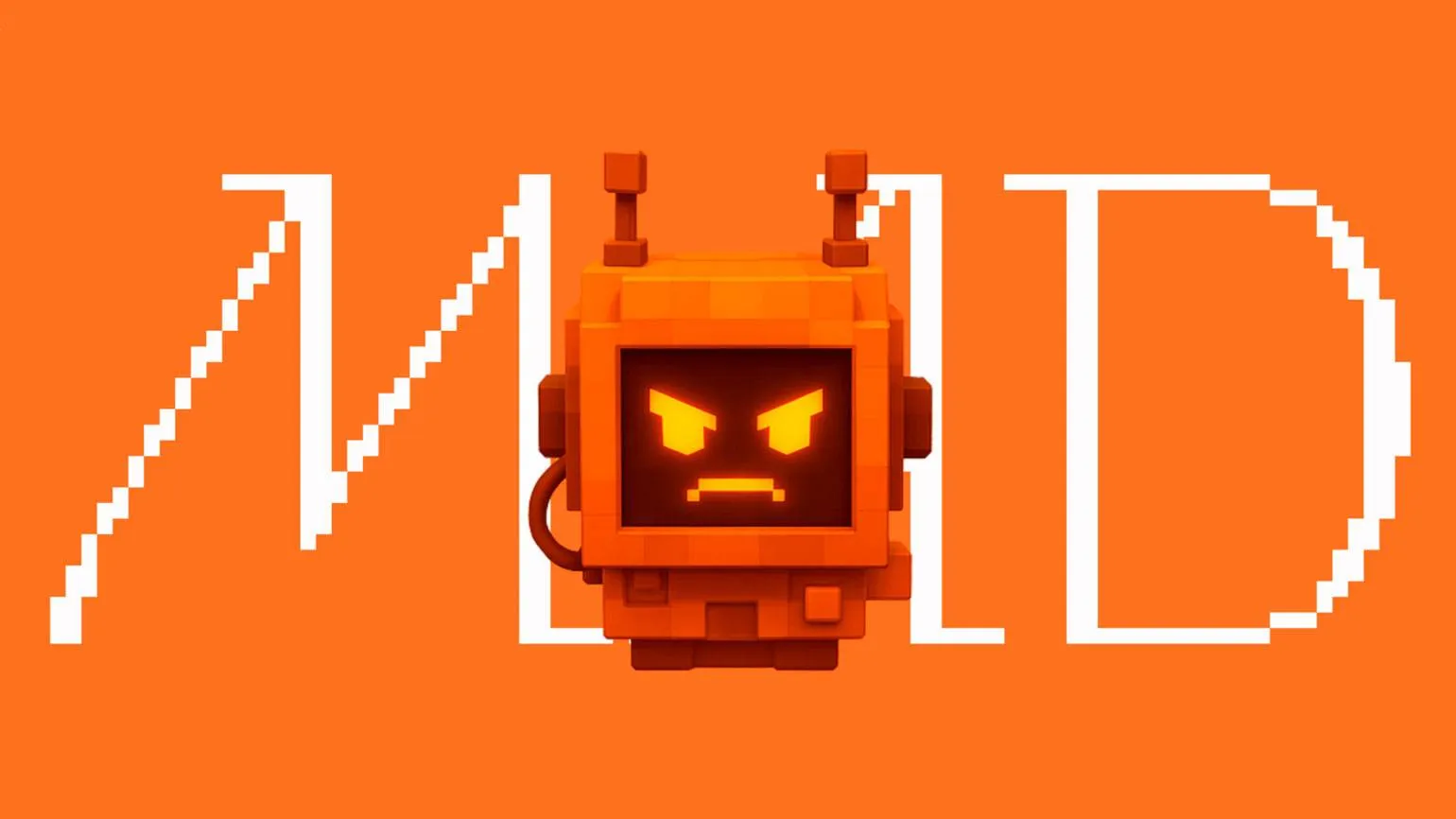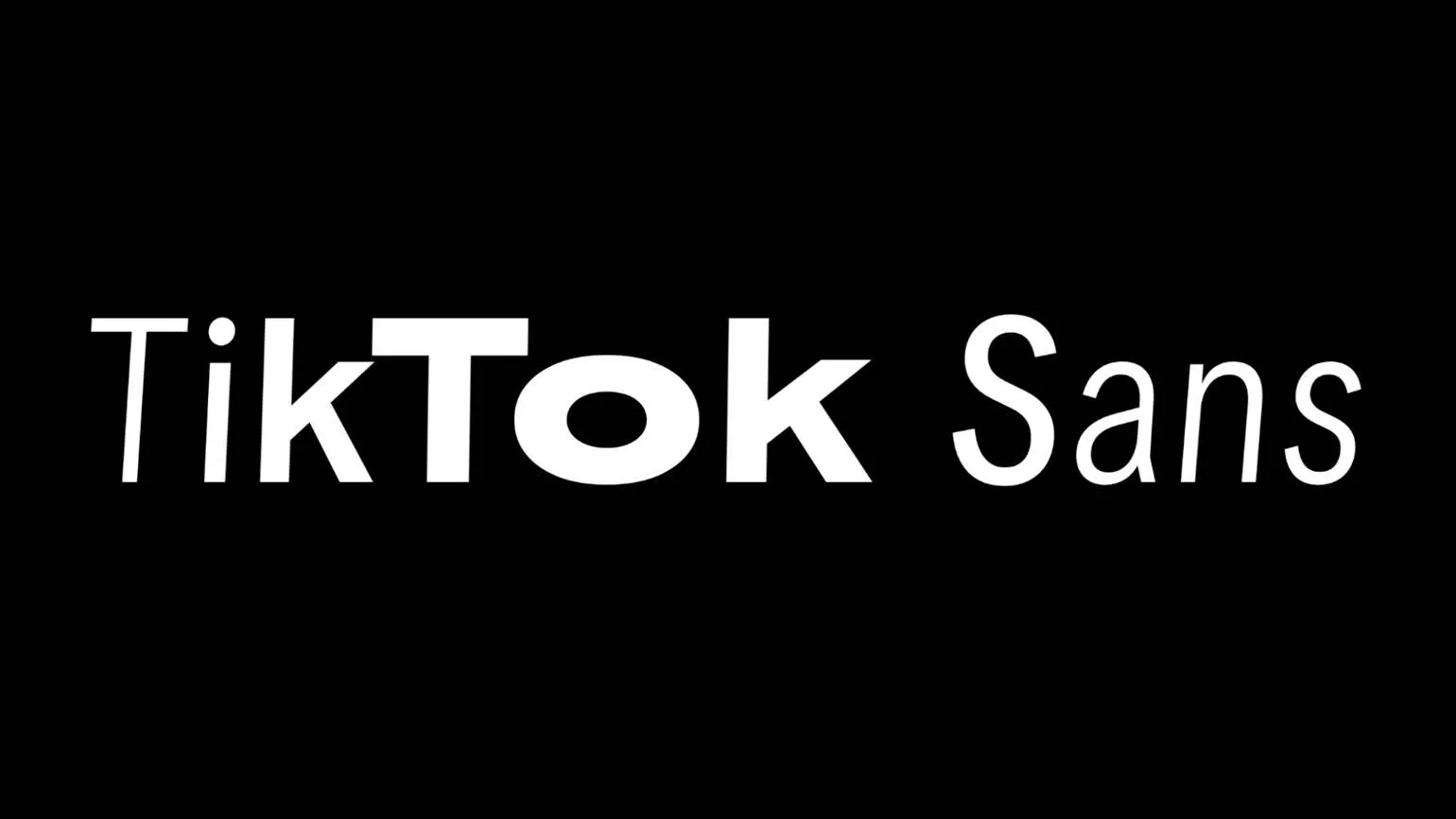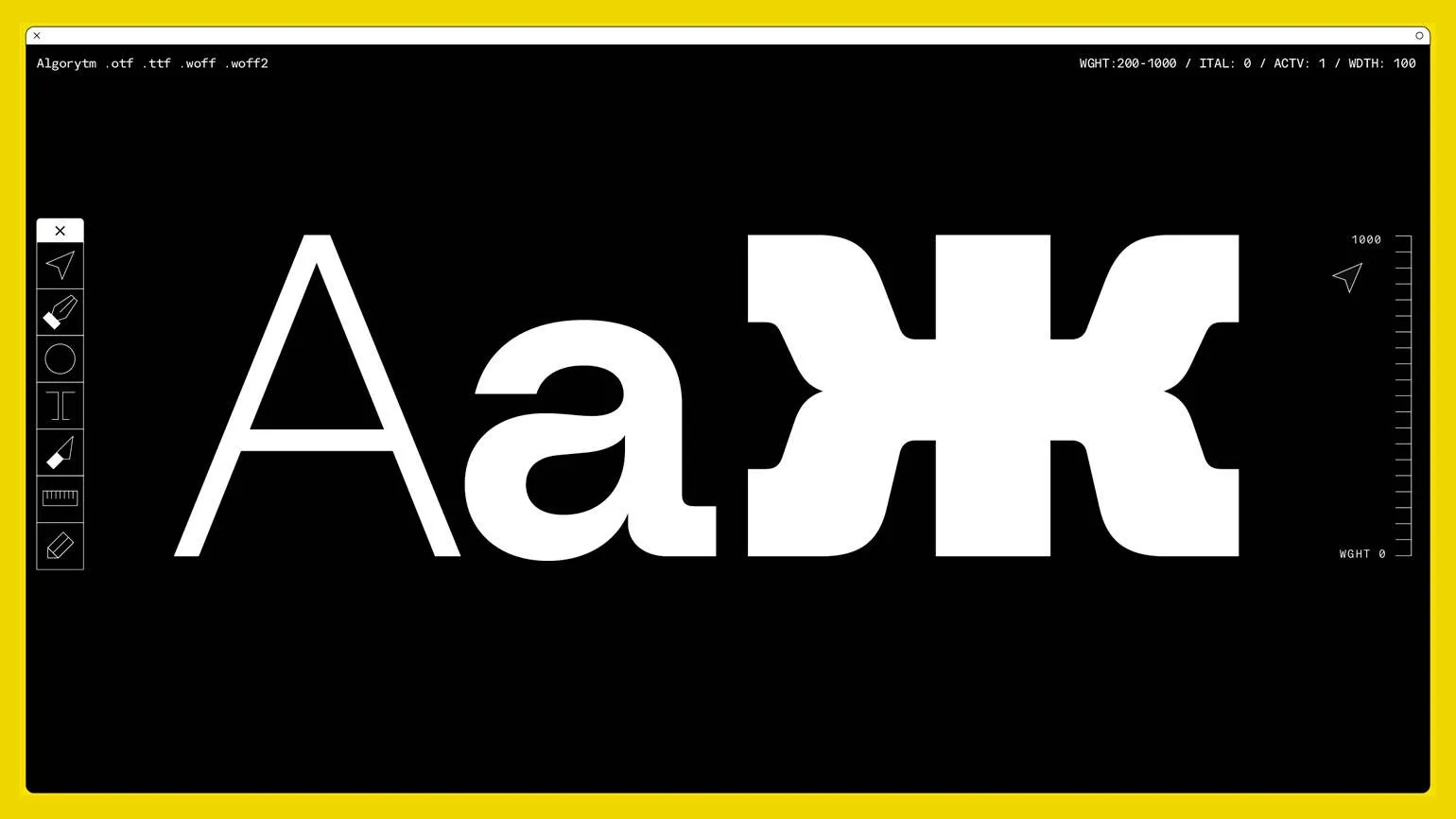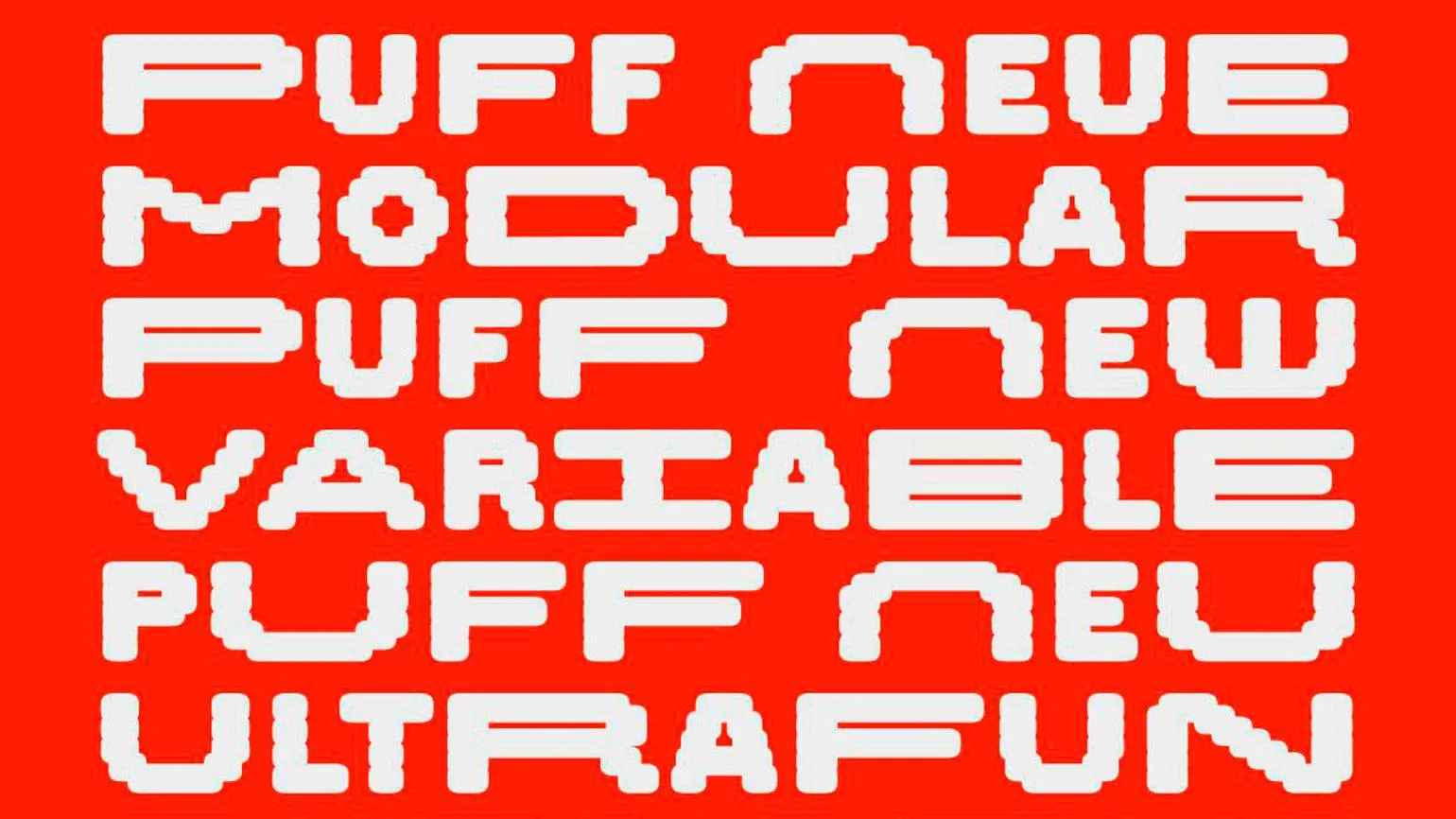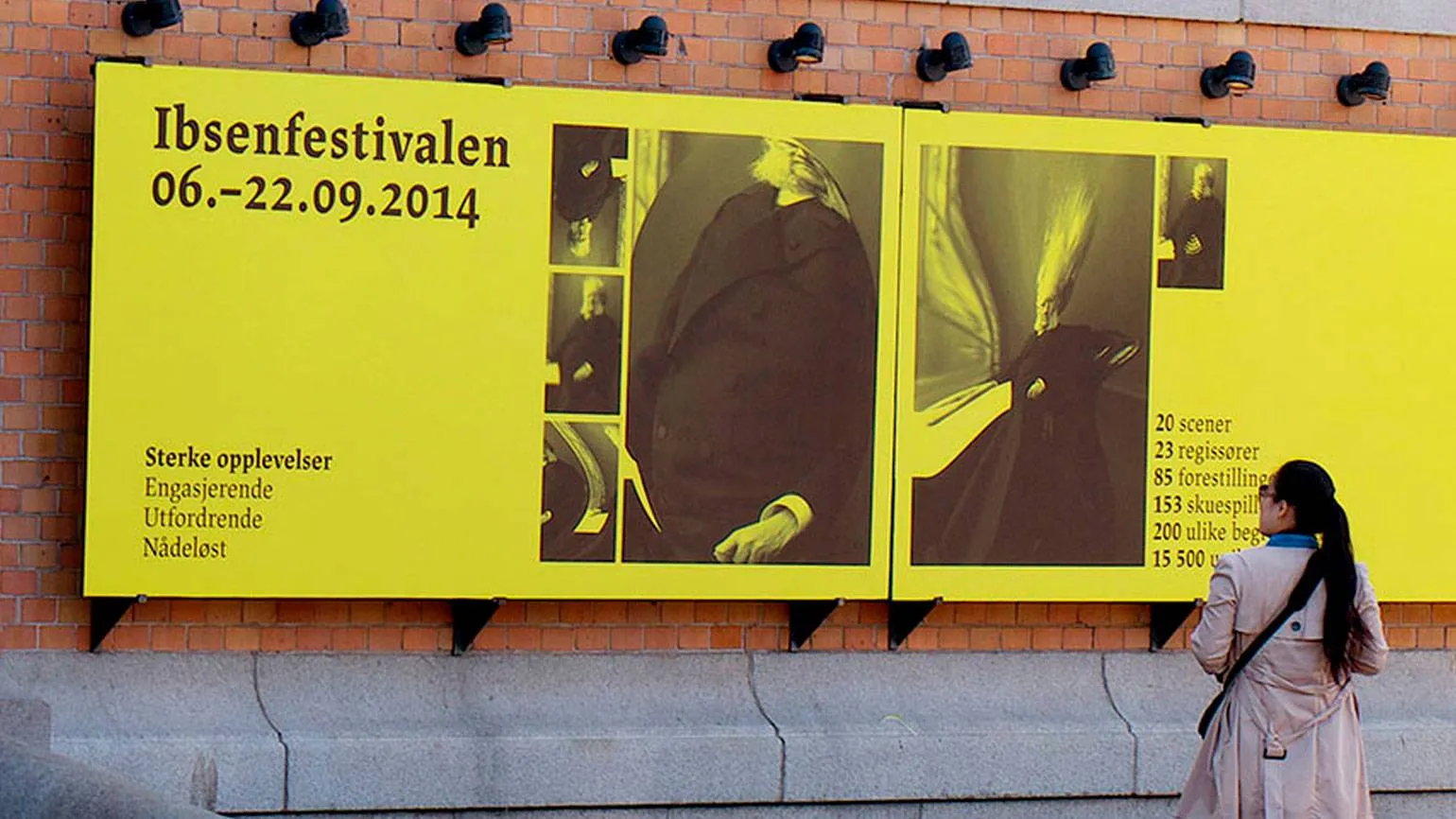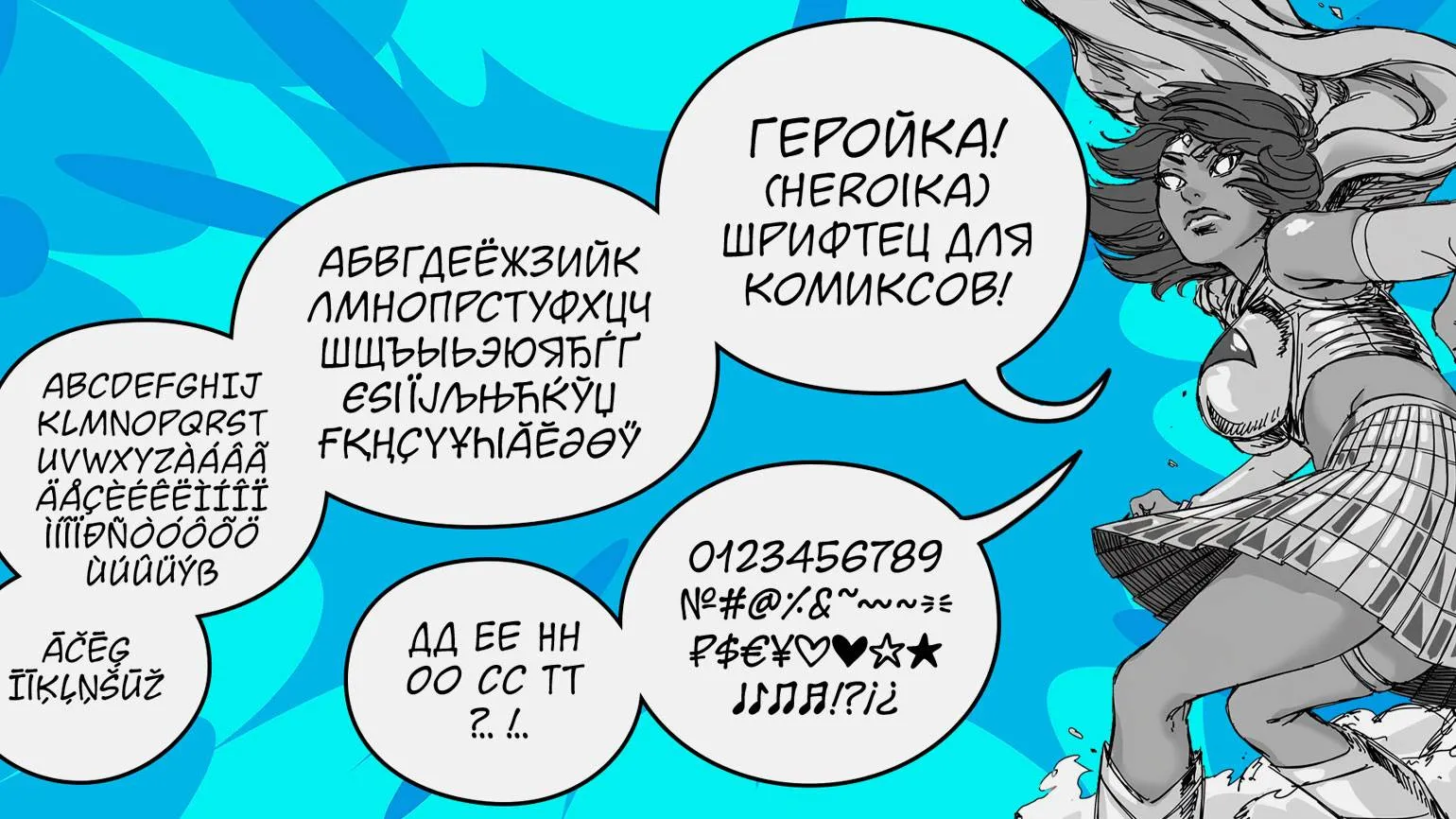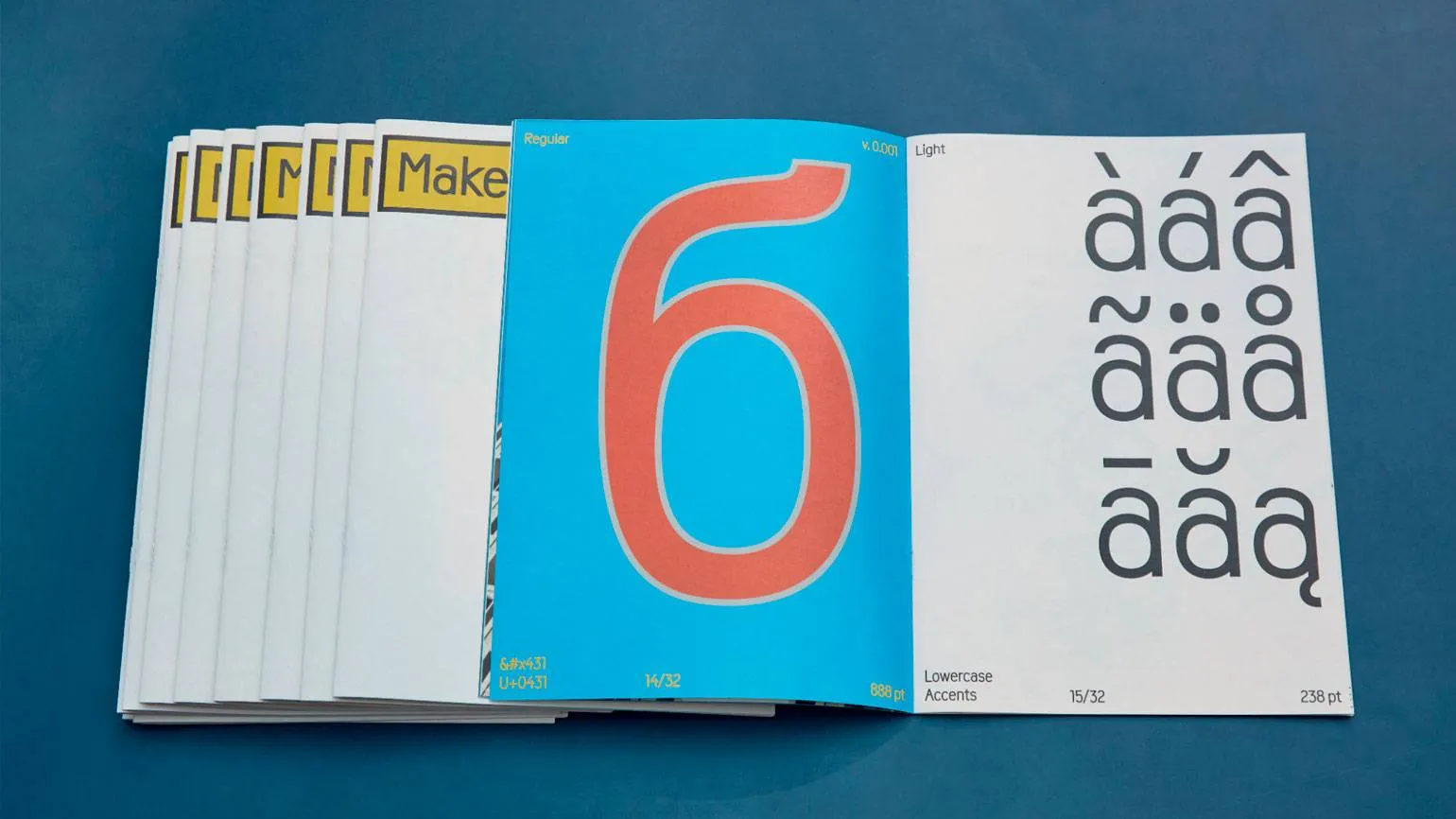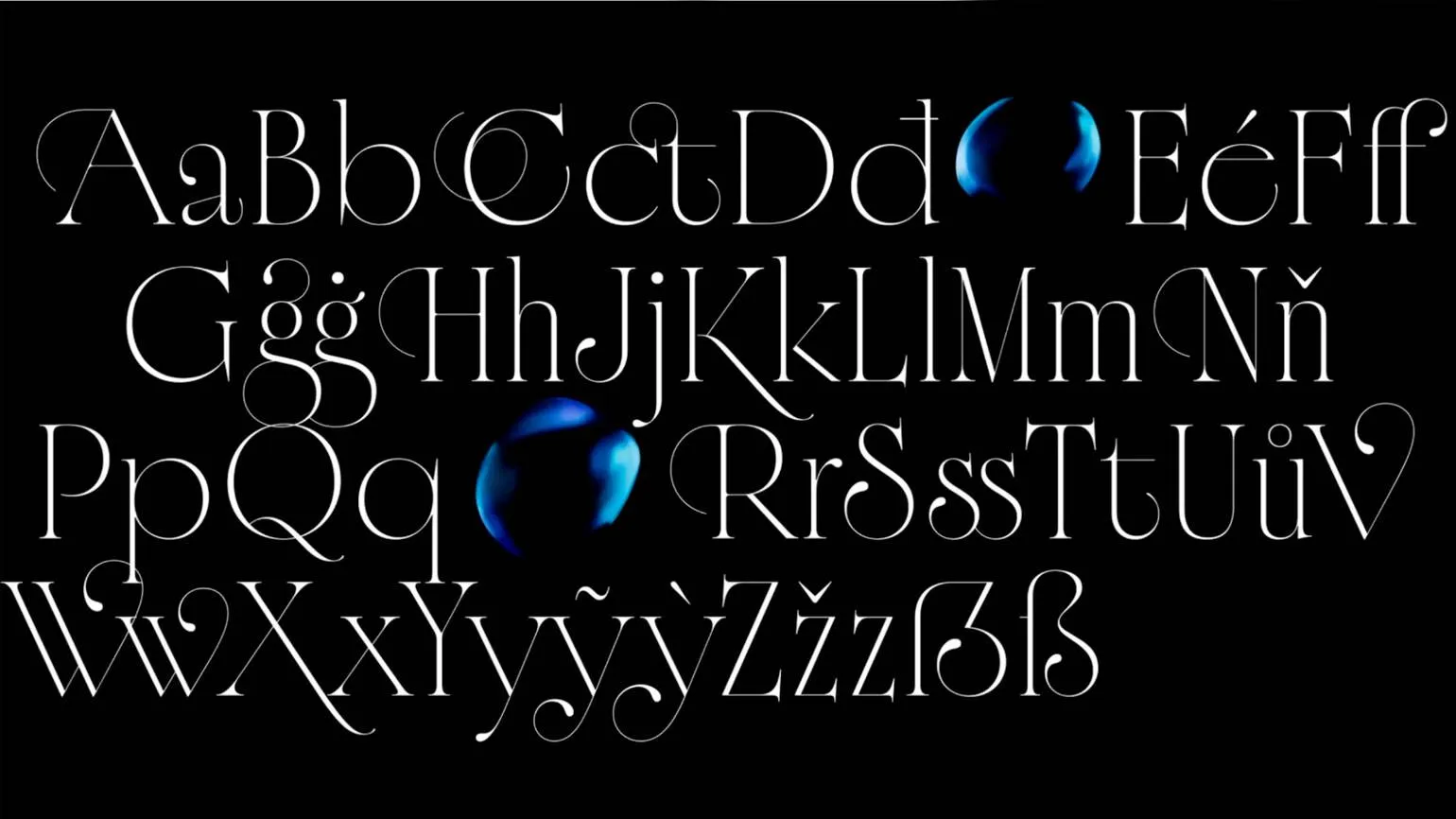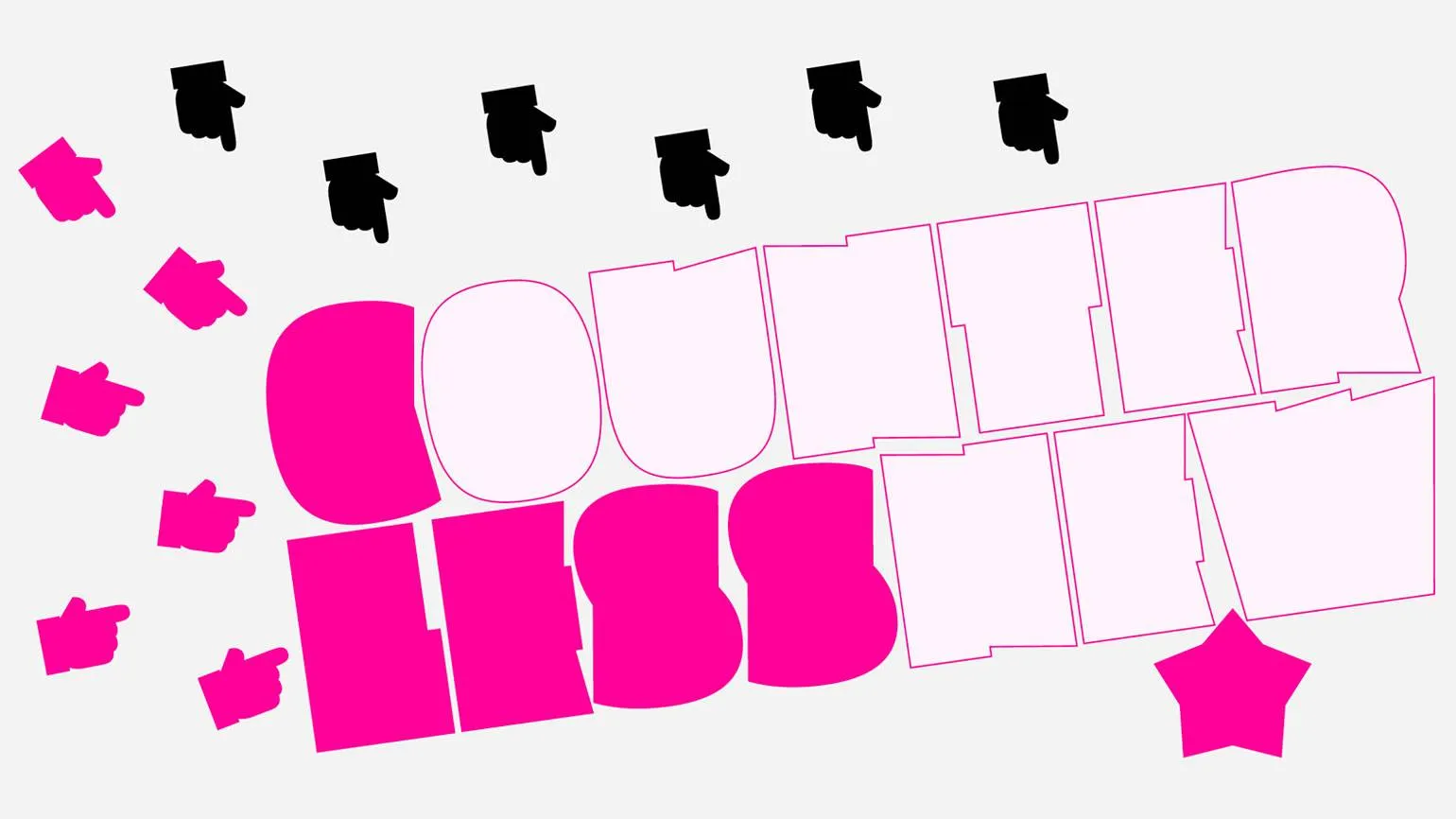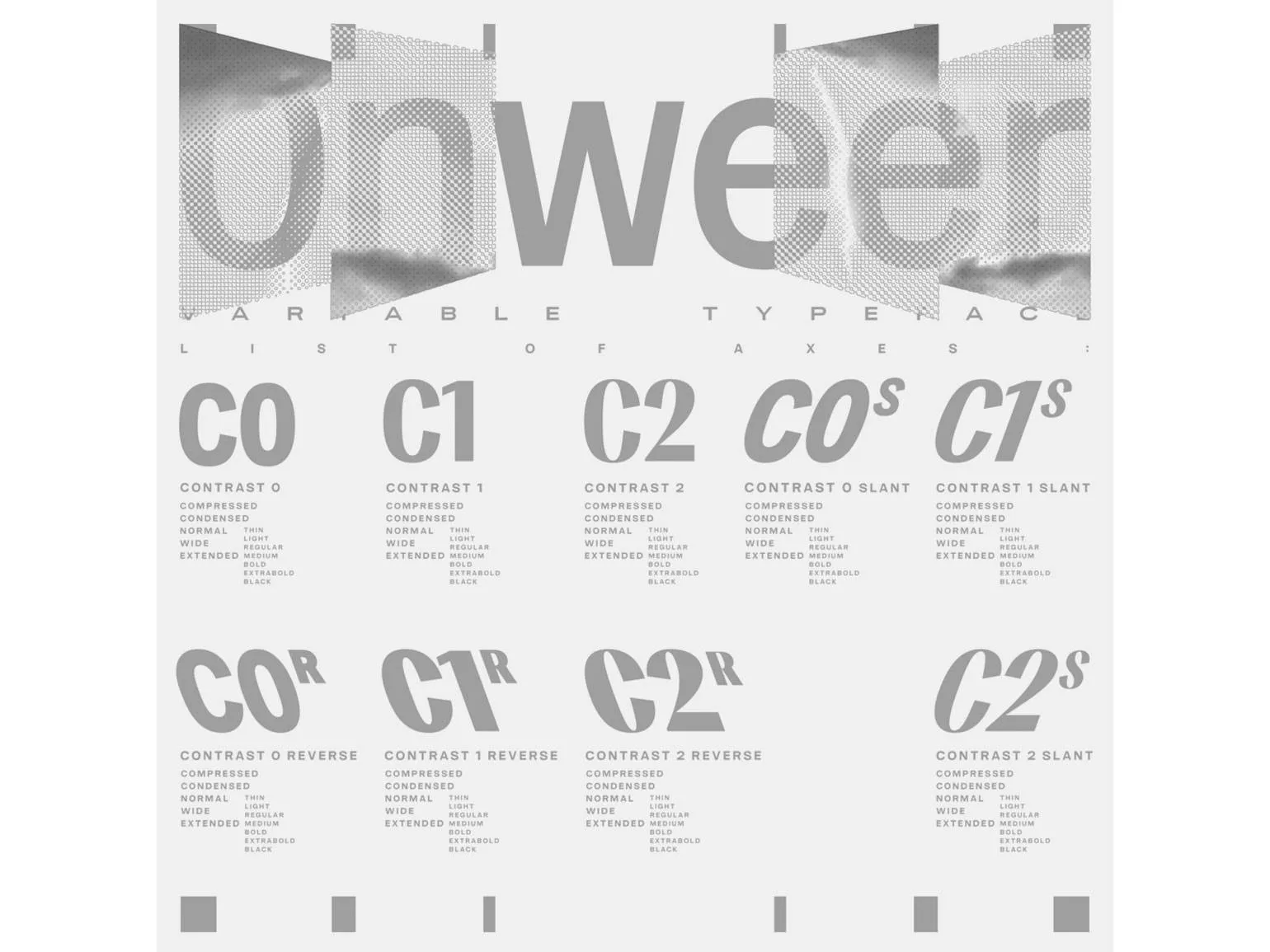
Лучшие шрифты 2025 года: стильные и актуальные тренды
Как бесплатные, так и платные варианты.
Мы подобрали самые актуальные шрифтовые разработки — как современные, так и классические, для особых случаев и повседневного использования.
Стиль, представляющий уникальный гротеск компании Evil Martians, основан на двух ключевых параметрах — ширине и интенсивности линий.
Сохраняет равновесие между легкостью и умиротворением. Подвешенные терминалы, закрытые отверстия и практически полное отсутствие контрастных элементов.
Состав включает в себя латинские и кириллические буквы, числовые символы, знаки препинания, дробные значения, валютные обозначения и прочие элементы.
Существует 63 различных стиля шрифтов, варьирующихся от тонкого (Thin) до очень насыщенного (Ultra Black), а также от сжатого (Condensed) до очень широкого (Ultra Wide).
По мнению разработчиков, этот шрифт является универсальным инструментом, который можно успешно применять в самых различных областях — от пользовательских интерфейсов до различных форм коммуникации.
Комиксы часто используют рукописные шрифты, чтобы передать непринужденность и индивидуальность персонажей. Такие шрифты помогают создать атмосферу, близкую к разговорной речи, и делают текст более живым и выразительным. Они придают страницам уникальный характер, позволяя читателям погрузиться в мир, который они представляют. Рукописный стиль создает ощущение непосредственности и близости, словно персонажи сами общаются с читателем.
Это именно то, как вы могли бы представить буквы, обрисованные спич-баблом в комиксах.
Состав включает в себя как расширенную латиницу, так и кириллицу. Также присутствуют различные знаки препинания, пиктограммы, несколько лигатур и другие элементы.
Существует четыре варианта начертания: обычный, жирный и их наклонные версии.
Этот стиль прекрасно подходит для оформления в духе комиксов и супергеройских сюжетов.
В определённых ситуациях рукописный шрифт может приобрести особую привлекательность.
Стиль характеризуется широким акцидентным гротеском, в котором наблюдается обратный контраст. Он объединяет геометрическую строгость с теплотой в мелочах.
Увеличенные диакритические знаки, округлённые элементы, перпендикулярные обрезы линий.
Состав включает в себя как расширенную латиницу, так и кириллицу. Также присутствуют знаки препинания, цифры в окружностях, валютные символы и другие элементы.
Seenonim отлично подходит для различных целей, включая создание брендового имиджа, разработку афиш, организацию коммуникации и формулирование крупных заголовков.
Он также способен справляться с небольшими текстовыми фрагментами в значительных объемах.
С этого года фирменный шрифт TikTok стал доступен для всех желающих. Это знакомый многим неогротеск, дополненный небольшими выразительными элементами.
Состав включает в себя расширенную латиницу, кириллицу, греческий алфавит, вьетнамский и множество других языков.
Содержит целых 168 фиксированных начертаний и предлагает четыре оси вариативности: насыщенность, ширину, наклон и оптический размер. Также включает различные полезные функции OpenType, болгарские альтернативы и многое другое.
Назначение этого шрифта в первую очередь заключается в его применении для субтитров в коротких вертикальных видео. Однако его возможности настолько разнообразны, что было бы неправильно ограничивать его только этим контекстом.
Это будет уместно в ситуациях, где не столь критично, чтобы шрифт ассоциировался именно с TikTok.
Автор: Родион Илюхин
Изображение: Родион Илюхин
Шрифт с модульной структурой и изменяющейся толщиной линий отличается высокой устойчивостью к деформациям благодаря своей лаконичной форме. Это современная интерпретация.
Состав включает в себя базовые латинские и кириллические алфавиты, а также цифры и минимальное количество знаков препинания.
Существует три разновидности по ширине: Regular, Wide и UltraWide. Вариативная модель предоставляет возможность точно настраивать ширину шрифта.
Puff идеально подходит для использования в качестве заголовочного шрифта на афишах концертов и вечеринок, а также в визуальной идентификации технологических компаний и упаковке товаров благодаря своей универсальности.